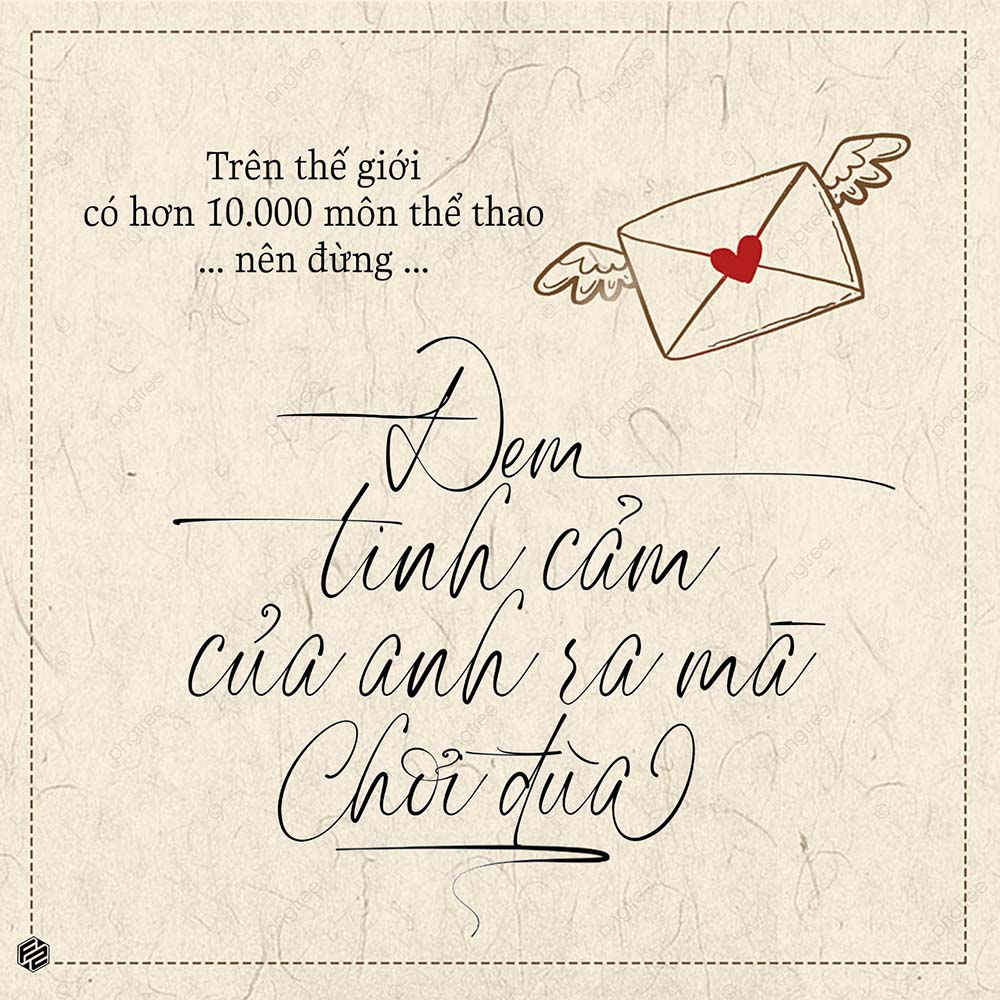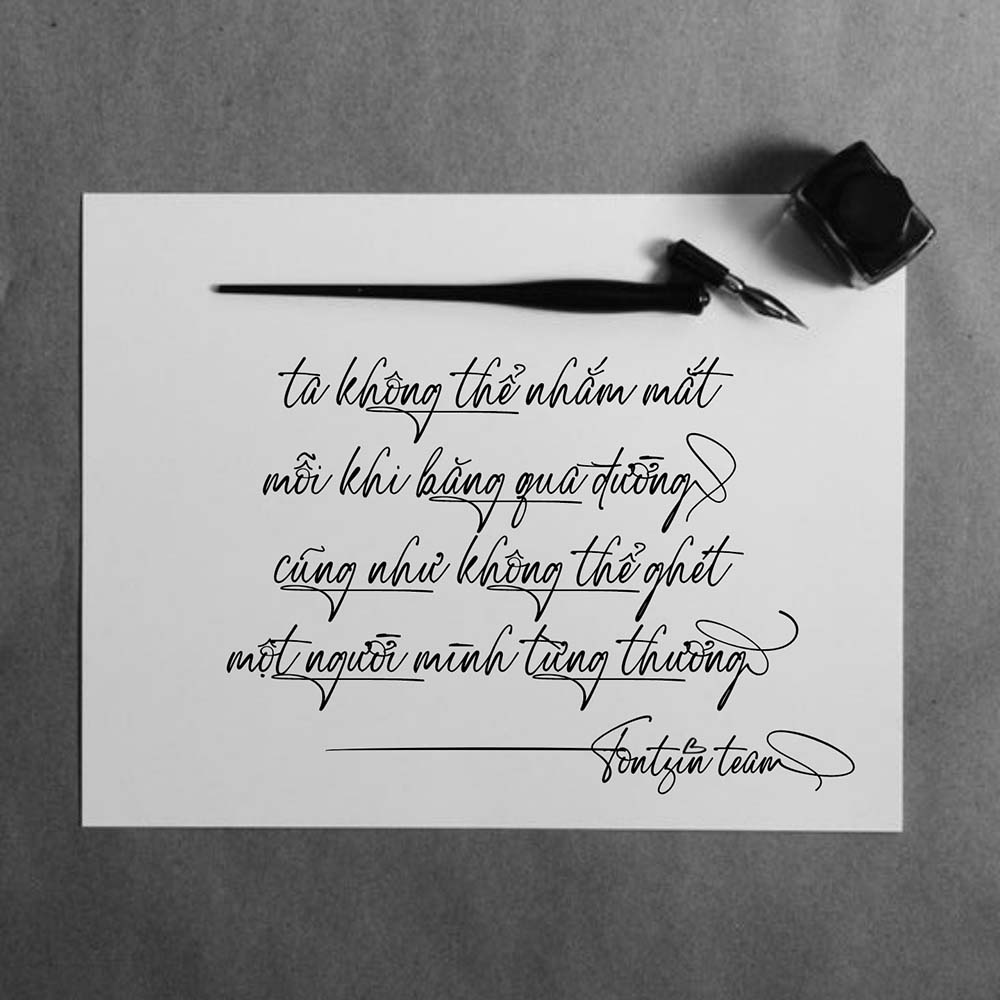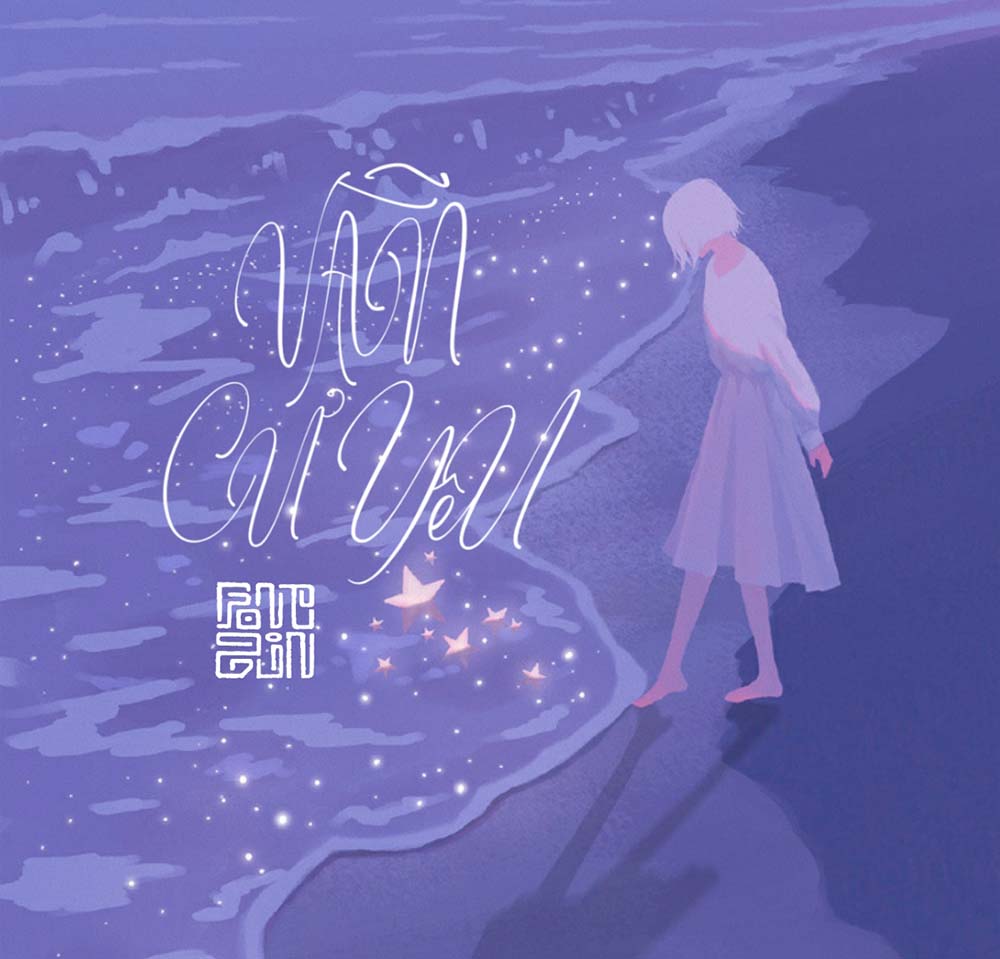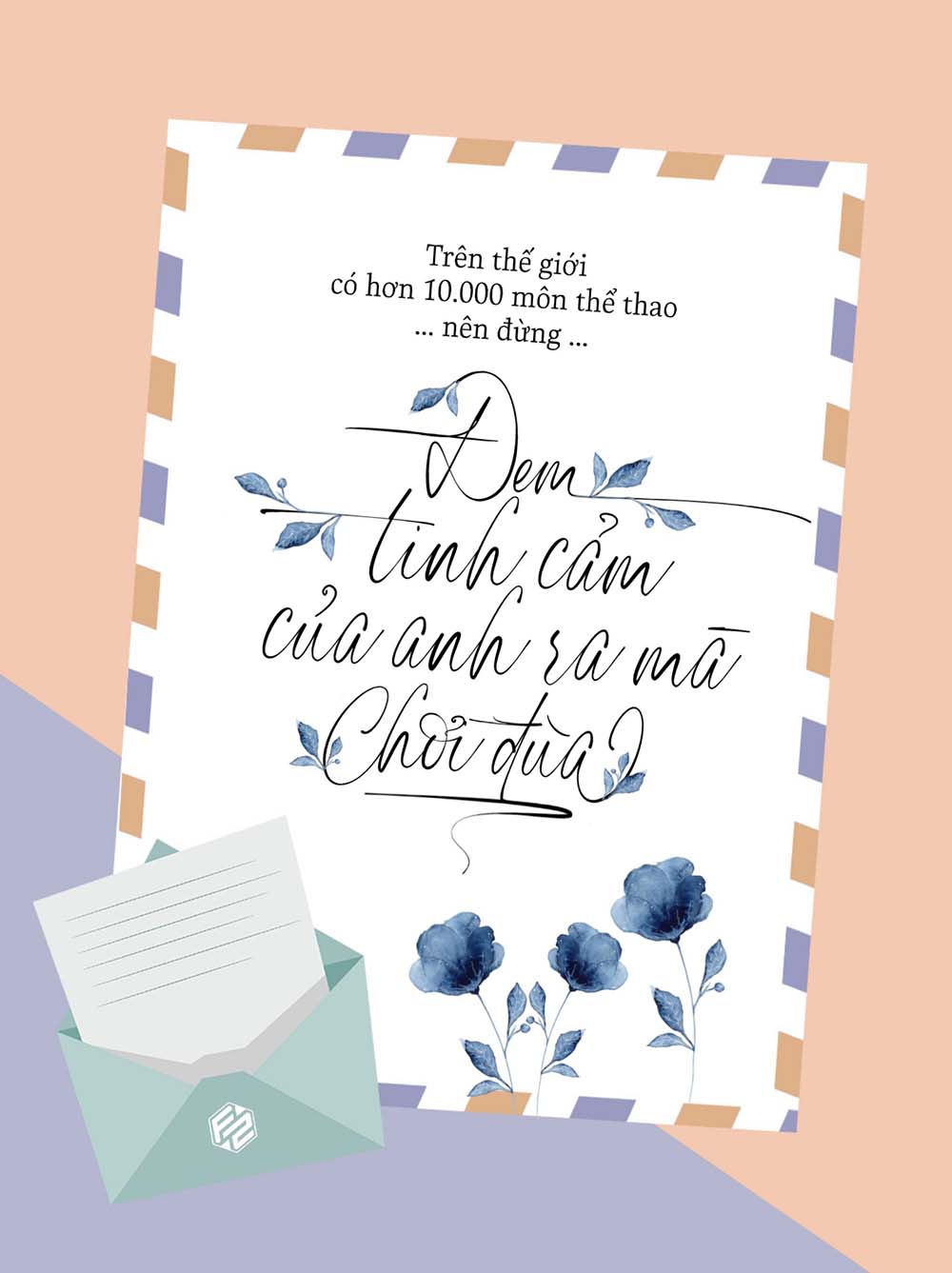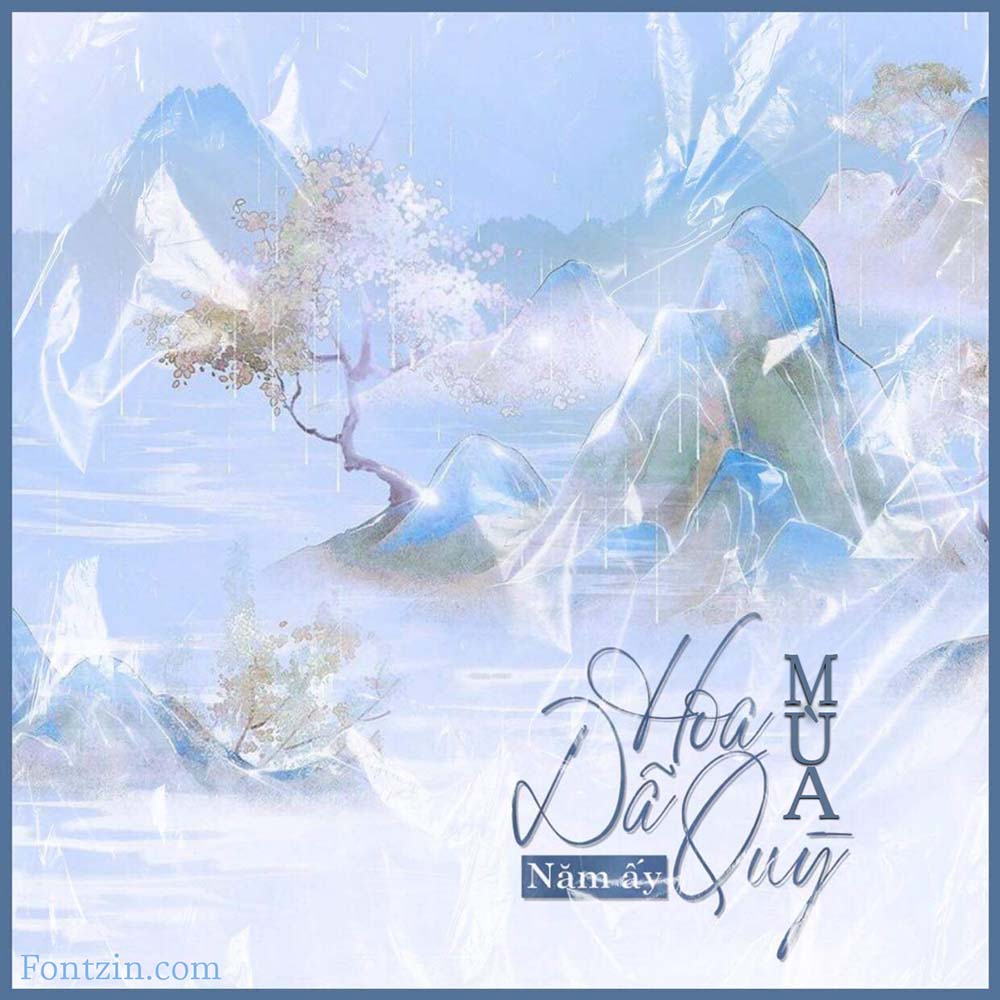
Font Việt Hóa - Jhodes Font Chữ Ký Đường Nét Mềm Mại Và Hiện Đại
Jhodes là một font chữ viết tay rất thanh lịch.
Font được thiết kế rất trau chuốt với các đường nét mềm mại, mảnh mai nhưng không kém phần bắt mắt, là một bộ font Handwritten không thể thiếu trong bộ sưu tập của bạn.
Font có nhiều glyph được thiết kế theo dạng chữ ký cá nhân, hoàn toàn phù hợp để tạo những ấn phẩm nghệ thuật mang dấu ấn cá nhân của bạn.